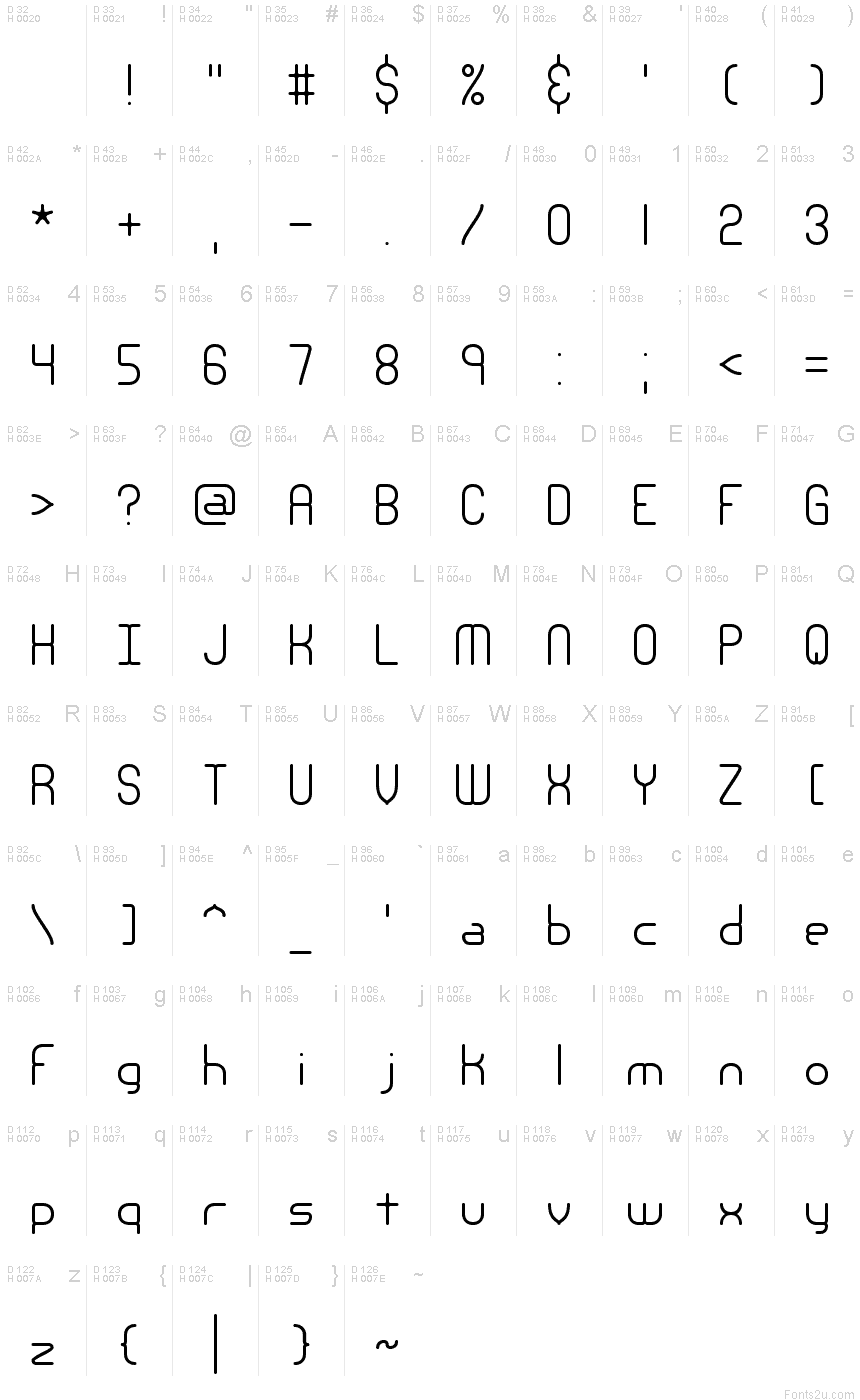
Nanosecond Thin BRK od ÆNIGMA FONTS to bezpłatny, futurystyczny krój displayowy o cienkich, zaokrąglonych liniach i geometrycznej, niemal przypominającej układ scalony strukturze. Formy zachowują gładki, rurkowy rytm z otwartymi łukami i uproszczonymi łączeniami, co nadaje projektowi techniczny, a nie odręczny charakter.
Nanosecond Thin BRK świetnie sprawdza się w tytułach sci-fi, brandingu technologicznym, nagłówkach plakatów, makietach interfejsów, okładkach albumów i motion graphics, ponieważ litery pozostają czytelne, zachowując swój unikalny styl. Ten darmowy font pasuje również do oprawy wydarzeń, logo i krótkich napisów, gdzie uproszczona linia pozwala przekazać komunikat bez zbędnych ozdobników.
Nanosecond Thin BRK